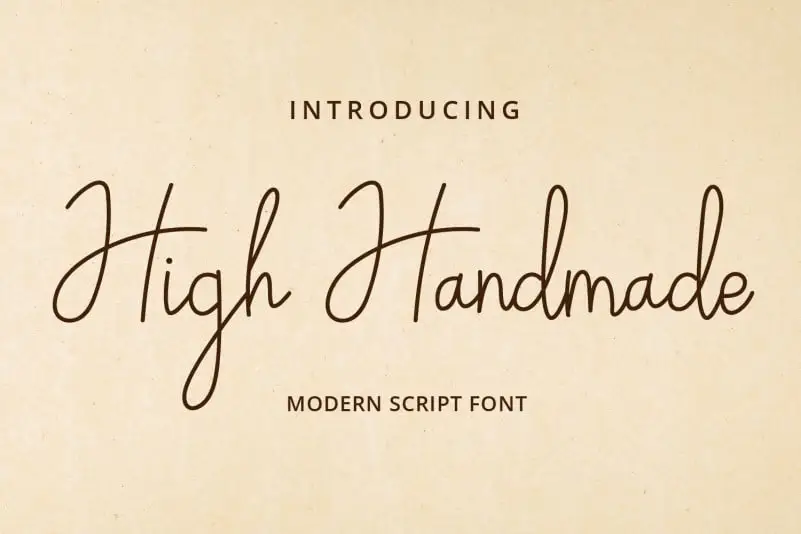
High Handmade Handwritten Font – Download Grátis
High Handmade Handwritten Font é uma fonte dedicada a quem aprecia a essência do escrita à mão, unindo elegância tipográfica com uma sensação atual e fresca. Criada por Planetz Studio, essa fonte mantém os elementos sofisticados da tipografia à mão enquanto oferece um toque contemporâneo que é perfeito para quem busca algo diferente e único. Se você procura uma fonte que dê mais vida a suas criações digitais, High Handmade Handwritten Font será o caminho certo para alcançar altos níveis de criatividade no design gráfico. Com seu charme autêntico, essa fonte é perfeita tanto para projetos profissionais quanto para expressões pessoais, tornando-a uma opção versátil e inspiradora em sua categoria.